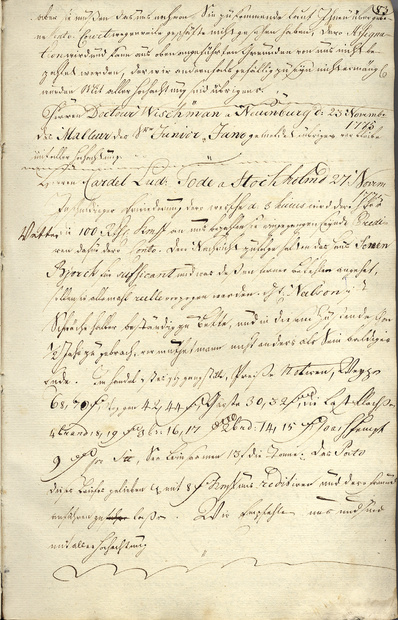
bitte um Hilfe. Ich bin eine Lettin, die einen Stellenangebot als Überstezer bekommen hat und als Test diesen Text "entziffern" muss. Ich bin beim surfen durch Internet auf dieses Forum aufgestossen und möchte um Hilfe bitten. Es ist sehr dringend! Ich bedanke mich im voraus!
Mal abgesehen davon, dass mich die Begriffe "Stellenangebot", "Test" und (kostenlose) "Hilfe" hier im Forum in dieser Zusammenstellung ein wenig irritieren, ist die Auflösung des Bildes selbst für einen erfahrenen Kurrentschrift-Leser nicht optimal. Ich kann spontan nur wenige Begriffe sicher entziffern, obwohl die Schrift insgesamt recht gut lesbar zu sein scheint. Bei einer besseren Auflösung könnte man mehr über den Inhalt sagen.
Hmm, Liuscorne, die Aufgabe einer Übersetzerin soll aber mE nicht sein, Texte zu entziffern sondern sie zu übersetzen. Damit hat die Anfrage hier durchaus Sinn.
Mazais: Das Sample ist viel zu klein und unleserlich für mich, um hier Hilfestellung anbieten zu können. Hast du das nicht größer bekommen?
Hmm, Liuscorne, die Aufgabe einer Übersetzerin soll aber mE nicht sein, Texte zu entziffern sondern sie zu übersetzen. Damit hat die Anfrage hier durchaus Sinn.
Für denjenigen, der die Stelle ausschreibt, gehört es aber offensichtlich zum Aufgabenspektrum, schwierige Vorlagen zu entziffern, sonst hätte er ja nicht einen solchen Text vorgelegt. Die Sache ist ethisch schon ein bißchen problematisch.
Zumal das explizit als "Test" bezeichnet wird. Sollten ähnlich schwierige Aufgabenstellungen nachher zum Arbeitsfeld gehören tut sich Mazais keinen Gefallen mit der Fremd-Entzifferung. Außer Stockholm und dem Datum kann ich eh nichts lesen.
danke für die Meinungen und Bemerkungen. Ich möchte mich entschuldigen und erklären, dass ich auf keine kostenlose Dienstleistungen warte. Ich stehe unter Zeitmangel, da ich dem potenziellen Arbeitgeber shon heute eine Antwort geben muss, ob ich diesen Text lesen kann und den Text erst gestern zugeschickt bekommen habe. Über den Inhalt weiss ich nichts. Unter anderem bin ich in diesem Forum zufällig auf ein ähnliches Hilfe-Ruf aufgestossen und habe verstanden, dass man sehr viel üben muss, um solche Texte zu lesen. Möchte auch einfach Meinung bekommen, ob es überhaupt möglich ist für mich als lettin, die zwar einen Deutsch-Philologe Diplom der Lettischen Universität hat, solche Texte fliesend zu lesen und was ich machen könnte um mich das anzueignen?
Das beigefügte Bild ist viel zu klein, um Dir eine vernünftige Antwort geben zu können. Da ist nichts zu erkennen, als daß es eine Kanzlei-Schrift ist, die wahrscheinlich sogar recht ordentlich geschrieben ist und einem Kundigen kein übermäßiges Kopfzerbrechen bereiten sollte.
… Möchte auch einfach Meinung bekommen, ob es überhaupt möglich ist für mich als lettin … solche Texte fliesend zu lesen und was ich machen könnte um mich das anzueignen?
Das hat nichts damit zu tun dass du Lettin bist, geschätzte 99,99 % der Deutschen können das ebenfalls nicht lesen. Was du tun kannst um dir das anzueignen? Üben, üben üben. Für einen Einstieg hab ich jene Seite auf die Schnelle gefunden, wahrscheinlich haben hier andere noch mehr oder bessere Tipps.
Danke für den Tipp und die webseite, ich bin damit 100% einverstanden, ich muss üben, üben und nochmal üben. Das Problem ist ja, dass ich dafür keine Zeit habe - der potenzielle Arbeitgeber hat mir bei der Aufgabe gefragt - kannst du das lesen? Wenn ja, treffen wir uns und sprechen weiter, wenn nicht - Danke schön! Auf wiedersehen!.... Aber die Stelle möchte ich bekommen, das werden auch andere Projekte sein, wo man als Übersetzer (deutsch-letisch-russisch) arbeiten muss und das würde für mich das Richtige sein. Ich weiss nicht was ich dem Arbeitgeber antworten kann.
P.S. ich könnte jemandem, der bereit wäre wenigstens einen Teil des Textes zu lesen, die File per e-mail zuschicken ich habe es in JPEG format erhalten, aber als Anlage in diesem Forum erscheint es wirklich sehr klein, weiss nicht (rein technisch) wie ich das vergrössern kann.
musst es ja nicht als leserlichen Anhang über das Forum machen.
Einfach hier und uns den Vollbildlink zur verfügung stellen ;)
Da brauchst du dir auch dann keine Sorgen über die Größe zu machen.
musst es ja nicht als leserlichen Anhang über das Forum machen.
Einfach hier und uns den Vollbildlink zur verfügung stellen ;)
Da brauchst du dir auch dann keine Sorgen über die Größe zu machen.
Danke, :-)
hierbei der Vollbildlink, ich hoffe, es funktioniert und erscheint als Vollbild
Ähem, ist vielleicht etwas naiv, aber warum fragst Du den potentiellen Arbeitgeber nicht nach dem Grund für so eine Aufgabe? Für den Aufgabenbereich den Du erfüllen kannst, scheint sowas in meinen Augen völlig irrelevant zu sein (ich kann das mit Sicherheit nicht lesen). Wenn das also spezifisch gefordert ist, dann stellt sich mir die Frage ob das nicht doch ggf. häufiger vorkommen wird, weil der Auftraggeber z.B. ein bestimmtes längerfristiges Projekt verfolgt. In dem Fall wäre das dann aber im Zweifelsfall im Moment nicht der richtige Job für Dich. Eine einfache Klärung der beiderseitigen Erwartungen könnte hier nützlich sein.
Das ist jetzt aber nur meine persönliche Meinung.
Hier nur mal ein schneller Versuch der ersten fünf Zeilen. Auch an Stellen, an denen die Schrift eigentlich ganz gut zu lesen ist, bräuchte ich mehr Einarbeitung, um den Rest entziffern zu können. Zumal es offenbar um geschäftliche Belange geht – es würde also nicht schaden, auch fachlich ein wenig Ahnung von Buchhaltung im 18. Jahrhundert zu haben.
Ein erfahrenerer Handschriftenleser wird hier aber wohl kaum Probleme haben.
aber sie müßen das uns nach von Sie [kann das stimmen?] zukommende laut Ihnen übergebene Conto ... geschäfte nicht gesehen haben, dero Assignation wird und kann aus oben angeführten Gründen von uns nicht bezahlet werden, die wir anderenfals gefällig zu seyn nicht ermangeln würden. Mit aller Hochachtung sind übrigens usw. usw.
Bearbeitet ( von Liuscorne)
... das Original noch einmal angeschaut
Jetzt hat mich doch das Interesse gepackt und ich habe mir das Blatt noch einmal angesehen. Der teilweise wunderlich unzusammenhängende Text scheint mehrere Briefentwürfe zu umfassen. Die ersten Zeilen gehören offenbar zu einem Brief, dessen Anfang nicht auf dem Blatt ist. Danach folgt der Entwurf eines Briefes an einen "Herren Doctour Wischman a Neuenburg d: 23. Novemb 1775", abgeschlossen mit der Grußformel "mit aller Hochachtung". Danach wiederum der Briefbeginn an einen "Herren Cardel[?] Lud: Tode a Stockholm d 27 Novem 1775"; auch hier steht am Ende die Grußformel "mit aller Hochachtung".
Dass es sich mehr oder weniger um Stichpunkte handelt, macht das Entziffern leider nicht einfacher.
Du tust Dir sicher keinen Gefallen, wenn Du den Text von jemand anderem übertragen läßt und dann dem Arbeitgeber sagst, Du könntest ihn lesen. Beihilfe zu diesem Betrug wird's von mir sicher nicht geben. Du bringst Dich damit doch nur selbst in Teufels Küche!
Warum sagst Du dem Arbeitgeber nicht, daß Du Schwierigkeiten hast, den Text zu lesen, es Dich aber durchaus interessiert und Du Dich daher sehr gerne einarbeiten würdest? Viele Mitbewerber, die das problemlos lesen können, wird es sowieso nicht geben.
Tausend mal Danke, ich komme schon langsam voran, übrigens, habe ich heute aus dem Telefongespräch mit dem guten Mann, der mir diese Aufgabe gegeben hat, erfahren, dass es in diesem Text Information über einen in der Ostsee versunkenen Schiff sich befinden soll. Ich bin auch richtig auf Geschmack gekommen, möchte diesen Text ganz "enträtseln". Aber diesen Stellenangebot werde ich wahrscheinlich eher nicht annehmen.
Trotzdem, herzlichen Dank an alle, die mir geholfen haben.
Du tust Dir sicher keinen Gefallen, wenn Du den Text von jemand anderem übertragen läßt und dann dem Arbeitgeber sagst, Du könntest ihn lesen. Beihilfe zu diesem Betrug wird's von mir sicher nicht geben. Du bringst Dich damit doch nur selbst in Teufels Küche!
Warum sagst Du dem Arbeitgeber nicht, daß Du Schwierigkeiten hast, den Text zu lesen, es Dich aber durchaus interessiert und Du Dich daher sehr gerne einarbeiten würdest? Viele Mitbewerber, die das problemlos lesen können, wird es sowieso nicht geben.
Ganz meine Meinung, genau das habe ich dem Arbeitgeber heute gesagt, dass ich damit Schwierigkeiten habe und noch viel Übung brauche.
Das war auch nicht meine Absicht in diesem Forum einen guten Mensch zu finden, der für mich diese Arbeit macht und ich die als meine verkaufe. Tut mir Leid, dass Sie so einen Eindruck bekommen haben
Das Problem bei Kanzlei bzw. Kurrent ist ja nicht unbedingt, dass es besonders schwer wäre das Lesen desselben zu erlernen, nur sind eben solche Schriftstücke dem Duktus des jeweiligen Schreibers unterworfen - manche schreiben sehr gut leselich, andere eher schlampig. Im schlimmsten Fall muss man sich Buchstabe für Buchstabe durcharbeiten. Ich hab auch noch etliche Texte meiner Großeltern und möchte mich wieder einmal auffrischen, in der Schule hatte ich Kurrent noch im Kunstunterreicht schreiben gelernt, aber seit Jahrzehnten nichts mehr gemacht.
Ja, die möglichen Probleme sind nicht viel anders als bei der lateinischen Schreibschrift. Da mangelt's ja auch nicht an „Sauklauen“, die man mühsam entziffern muß.